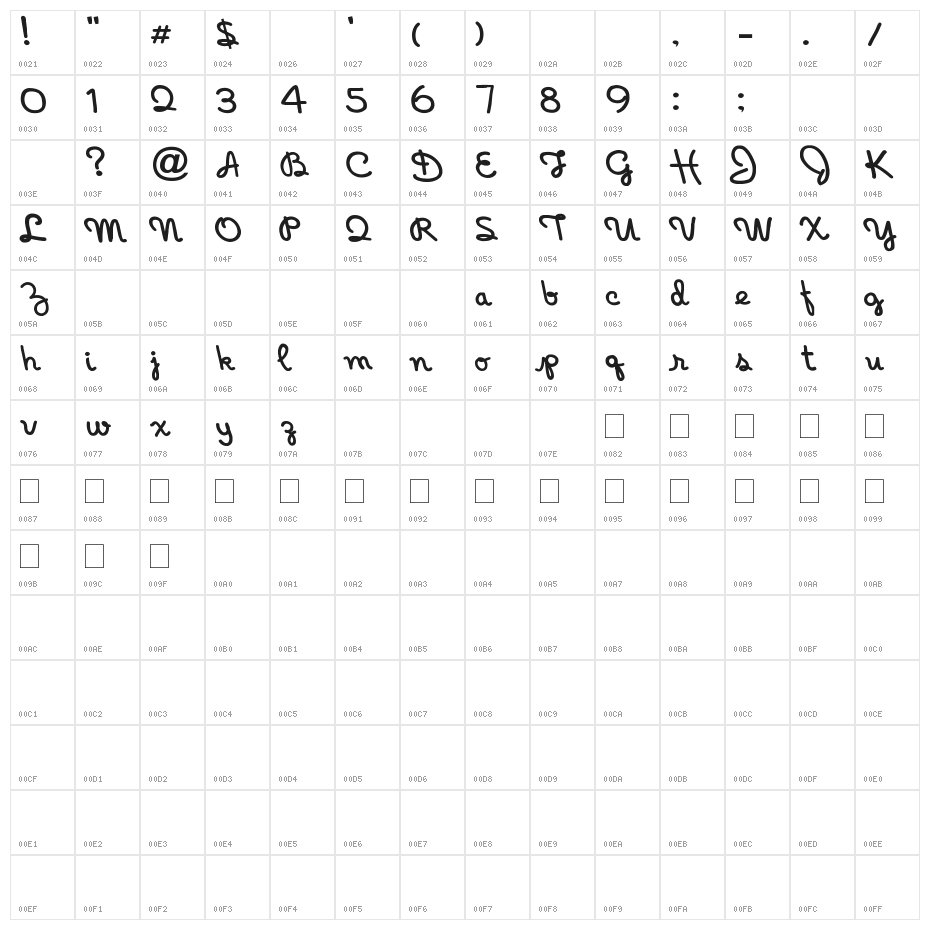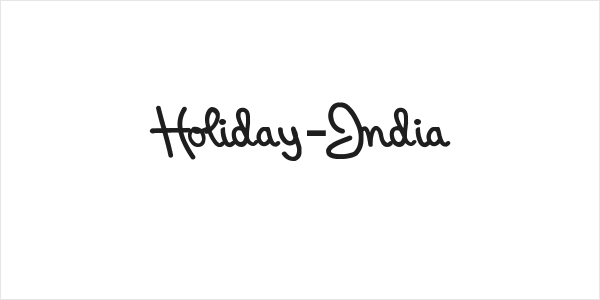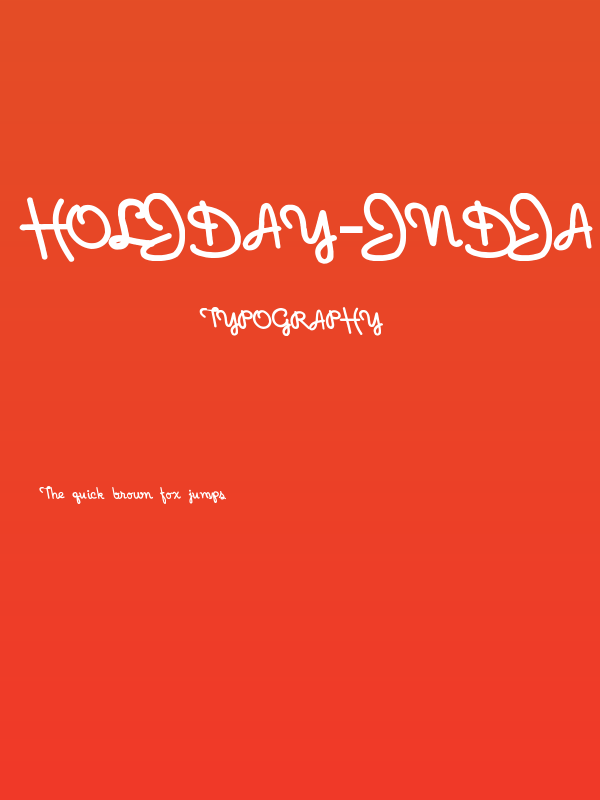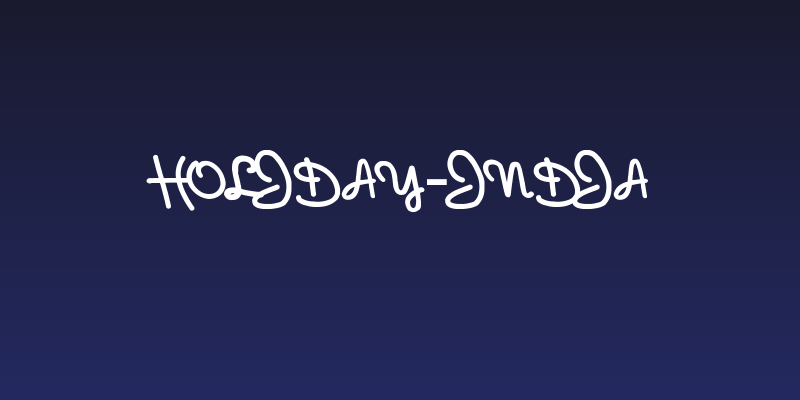
Holiday-India Font
| Caso d'uso | Logos, Headlines, Invitations |
| Progetti proposti | Ideal for greeting cards, children's books, playful branding, and casual invitations. |